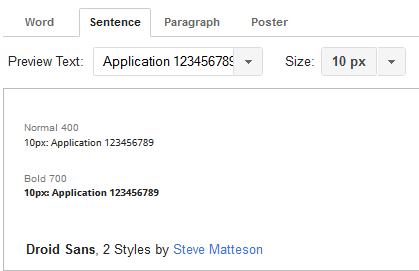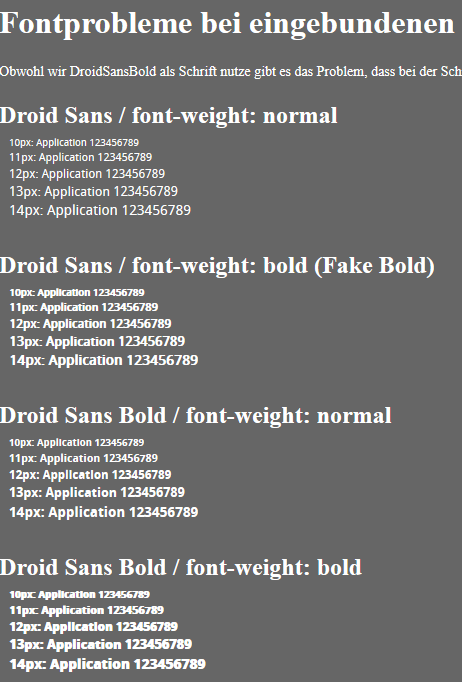
Probleme mit Droid Sans: Schriftdicken
Ich wollte mal kurz eine Frage loswerden und hoffe, das der ein oder andere da eventuell schon das selbe Problem hatte.
Wir benutzen Droid Sans für diverse Web- und Desktopanwendungen und was langsam problematisch wird, ist der Einsatz einer fetten Variante. Benutzt man die geHTMLte Boldvariante ergeben sich einfach hässliche Buchstaben. Benutzt man hingegen einen fett heruntergeladenen Font, dann treten hier teilweise unschöne Dinge auf, wie Verschmelzung von "i" und "i-Punkt". "a" und "e" laufen zu, ebenso wird die 7 recht kacke dargestellt. Ich nehme stark an, dass wir die Fonttechnologie noch nicht recht überrissen haben, da ja Droid Sans als Screenfont angepriesen wird.
Habt Ihr gute Tipps auf Lager oder brauchbare Schriftdickengrade? Ach ja, hab eine Datei angehängt!
betrifft die anzeige alle browser?
wie ist die schrift eingebunden mit festen werten oder kruden werten?
bei der vorschau von google webfgonts wird der font sauber bi 9 px dargestellt.
Es betrifft gerade Werte wie etwa 12 und 14 pt. Es wurde auf mehreren Browsern getestet. Ich frage aber nochmal genau nach, wie die Einstellungen waren. Auf jeden Fall war die Maschine ein PC, bei mir aufm Mäc schaut's auch ganz okay aus. Vielleicht haben wir das irgendwie blöd eingebunden, denn bei den Desktopanwendungen liegen sie auf nem Server. Aber da dürfte doch nichts schiefgehen, so rein aus meinem Grundverständnis!
Nachsatz: Also die Probleme tauchen bei lokaler Schriftablage heraus auf. Browser glaub ich Chrome und Firefox
Leider habe ich grad nur Screenshots, DA mein Kollege die Umsetzung macht, der Tipp mit der doppelten Fettung ist schon nicht schlecht, aber die müsste sich dann reingeschlingelt haben. Die Fonts sind folgendermaßen eingebunden: Droid Sans 700 (fett), die Schrift wird dann aber per CSS als normal aufgerufen - damit der Schriftschnitt halt erhalten bleibt.
Generell verfügen nur ca. ein Drittel der Google Fonts über ein Hinting und von diesem Drittel sind die meisten »auto gehinted«. Die Darstellung bei verschiedenen Punktgrößen wurde also automatisch generiert und seltenst manuell optimiert, somit kann es also zum einen Unterschiede bei der Darstellung zwischen verschiedenen Größen geben.
Generell ist natürlich auch ein Web Font nicht für eine Desktop Anwendung gedacht, was im Falle derer somit also ebenfalls zu Problemen führen kann.
Der Faux-Bold (den fetten Schnitt nochmal via CSS extra auf fett setzen, oder ein falsches »weight« benutzen) ist auch zutreffend.
Danke schonmal, also die Anwendungen werden dennoch über den Browser aufgerufen - insofern sollte das keine Rolle spielen - die Dateien bleiben ja die selben. Wenn jemand noch eine gute Idee hat, freue ich mich. Wenn nicht, würde ich mich Anfang nächster Woche noch einmal mit einer Testseite melden.
Eine eigene Testseite solltet ihr auf alle Fälle bauen, einfach um zu überprüfen, ob an eurem Ende irgendetwas schief gelaufen ist. Die könnt ihr dann z.B. hiermit vergleichen: http://typecast.com/preview/google/Droid%20Sans
Wenn ihr einmal dabei seid, kuckt euch die Noto Sans (eine besser ausgebaute Droid) am besten auch noch an: http://typecast.com/preview/google/Noto%20Sans
Bei mir läuft die Noto Sans in Typecast übrigens etwas weiter als die Droid. Ansonsten sehen beide fett auch in kleinen Graden so aus, wie ich es erwarten würde.
wie angedroht folgt hier die Testseite für das Droid Sans-Problem. Ihr müsst, um das Problem erfassen zu können, die Droid sans in den angegebenen Schnitten bei Euch lokal installiert haben. Ich freu mich auf Euren Input:
So sieht es bei mir unter Windows und Firefox 26 aus.
von Droid Sans Bold / font-weight: bold würde ich abstand nehmen, das kann nicht gut aussehen. aber du hast recht, generell siehts nicht so toll aus, denn in google webfonts sieht der font so bei mir aus:
ich bin aber zu wenig programmierer um in deinem css auf anhieb einen fehler zu erkennen.
Es scheint, ihr habt die Webfonts über Fontsquirrel generiert und dabei wohl das Original-Hinting durch Auto-Hinting ersetzt.
Ansonsten ist das auch einfach ein grundsätzliches Problem: Fette Schrift in 10 oder 11 Pixeln. Da versagt die Automatik dann irgendwann und es hilft nur noch Delta-Hinting wie bei den MS-Core-Fonts.
Natürlich muss die Droid Sans bei uns nicht lokal installiert sein, das würde ja das Prinzip Web Fonts ad absurdum führen
Ich würde die Droid Sans nicht "lokal" (auf dem Web Server) speichern, sondern die von Google gehostete Version bevorzugen, also auch entweder via CSS oder Javascritp einbetten. So kann man nicht mal sagen, ob die Version bei euch wirklich der aktuellen Version von Google entspricht und vergleicht eventuell Äpfel und Birnen. Außerdem stellt ihr so sicher, das ihr auch immer die aktuelle Version der DroidSans einbindet, da diese eventuell ja auch erweitert oder optimiert wird.
Ihr müsst, um das Problem erfassen zu können, die Droid sans in den angegebenen Schnitten bei Euch lokal installiert haben.
Ne. Deine Test-Seite verlangt nach Schriften namens DroidSans und DroidSansBold. Selbst wenn die Einbindung der Webschriften vom Server nicht klappt, dürften die Chancen, lokal installierte Droids zu nutzen, schlecht stehen. Bei mir muss ich eine lokal installierte Droid Sans als 'Droid Sans' einbinden (mit Leerzeichen!), damit es funktioniert.